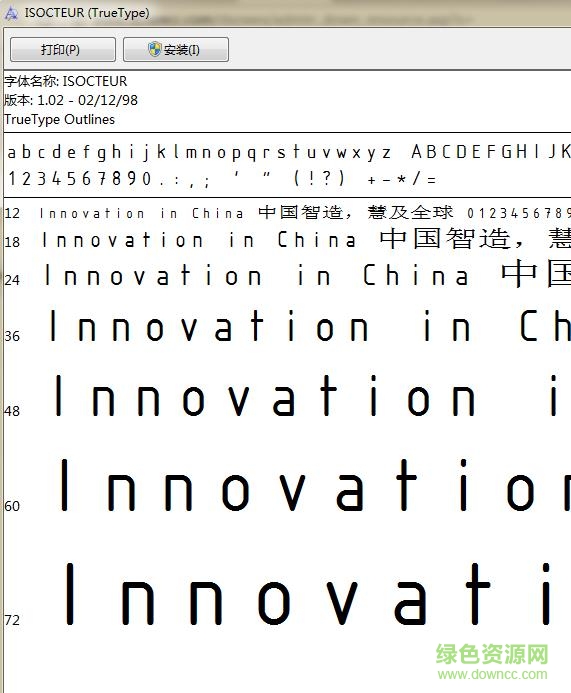
isocteur字體是一款十分有趣的英文字體,這款字體的字體效果將讓你感受到優(yōu)雅的視覺享受,每一個(gè)字母都十分圓潤,用戶寫作過程中將讓人賞心悅目,快來綠色資源網(wǎng)下載吧!
字體的樣式很不錯(cuò)哦,我用的時(shí)候感覺我在文檔中打出的每一個(gè)英文單詞都很可愛,真是一款十分不錯(cuò)的字體,我可以用一年!
2、這款字體簡(jiǎn)單易懂又有意思,一般用于導(dǎo)視系統(tǒng)設(shè)計(jì)領(lǐng)域